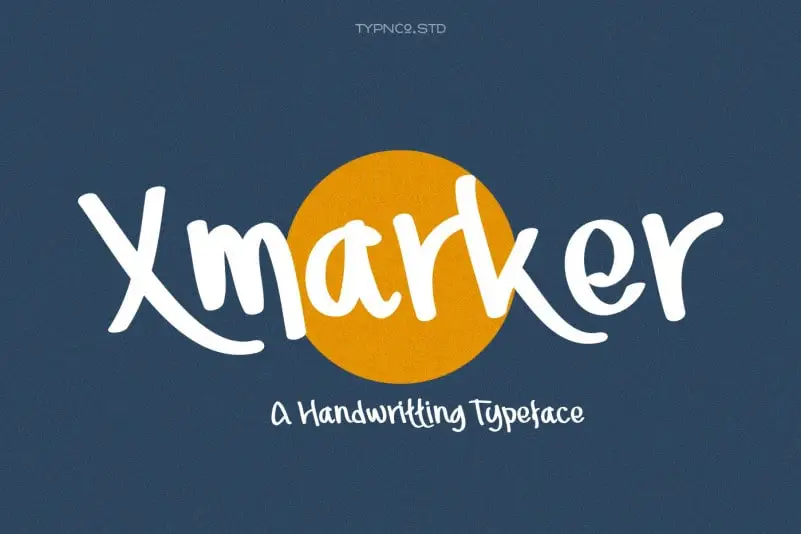
Xmarker Script Font – Download Grátis
A Xmarker Font é uma fonte de script feita à mão, projetada para entregar um toque autêntico e criativo aos projetos digitais. Inspirada na escrita a lápis manuscrita, essa fonte Brush oferece letras estilizadas e elegantes, perfeitas para aplicar em variados formatos de design. Seja para criar logotipos sofisticados, adesivos de nome tag, citações handwritten para embalagens ou materiais promocionais, cartões de agradecimento ou até mesmo postagens no Instagram e redes sociais, o Xmarker é uma escolha ideal. Com uma ampla gama de letras maiúsculas e minúsculas, símbolos de pontuação variados e suporte multilíngue, esta fonte oferece flexibilidade para atender a necessidades específicas. Ela também inclui números romanos e caracteres especiais que podem ser usados como o momento da criatividade desejado permite. A Xmarker é perfeita tanto para designers digitais quanto para profissionais de comunicação visual, oferecendo um estilo único capaz de destacar seus trabalhos. Com uma variedade tão grande e variada, a Xmarker pode ser usada em qualquer projeto que busque um toque autêntico, criativo e singular.